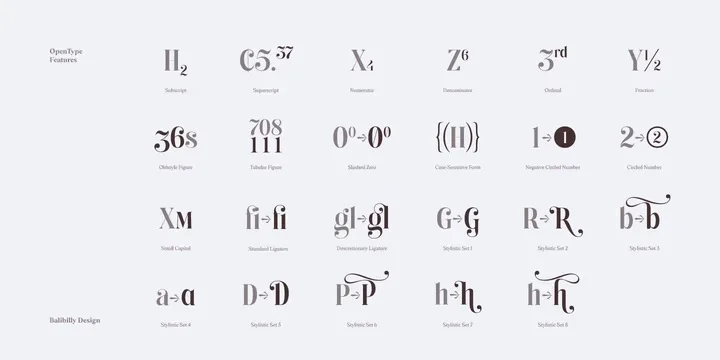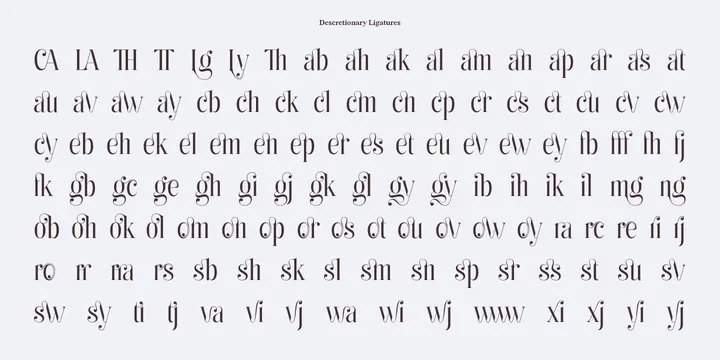
Font Kage Pro Việt hóa sáng tạo, thanh lịch nhiều glyph cực đẹp
Nếu bạn đang tìm kiếm một font chữ cổ xưa nhưng vẫn mang ấn tượng sâu sắc cho người nhìn và tăng phần sang trọng cho thiết kế của bạn thì bạn không thể bỏ qua cách tải Font Kage Pro Việt hóa do IoTStartUp chia sẻ trong bài viết này nhé.
Giới thiệu Font Kage Pro
Điểm khác biệt ở Font Kage Pro Việt hóa chính là được lấy cảm hứng thiết kế từ thế kỷ 18 cổ xưa cùng sự tương phản trong font chữ và các phong cách serif làm cho Font chữ việt hóa thêm ấn tượng và thanh lịch hơn.
Có thể nói rằng font Kage Pro này có liên kết mật thiết với thiết kế thời trang Châu Âu và Toàn cầu, những thiết kế sử dụng font Kage Pro đều được đánh giá cao về sự linh hoạt, động đáo và sự phá cách trong thiết kế chung.
Font Kage Pro được thiết kế tỉ mỉ với các đường nét mượt mà phù hợp cho rất nhiều các thiết kế khác nhau như sản phẩm, thời trang, tạp chí, typography, quảng cáo...
Các chuyển đổi của Kage Pro đều nhẹ nhàng cho nên khi sử dụng thì bạn nên định vị lại và tăng kích thước của font chữ lên nhé, vừa đẹp lại không làm ảnh hưởng đến thiết kế.
Đặc biệt, Kage Pro Font Family có 22 kiểu trong đó có 11 kiểu upright và 11 kiểu oblique từ Thin đến Black, ấn tượng hơn là mỗi kiểu có đến 1.655 glyph vì vậy mà bạn tha hồ sáng tạo để tạo ra những thiết kế ấn tượng và hoàn hảo hơn.